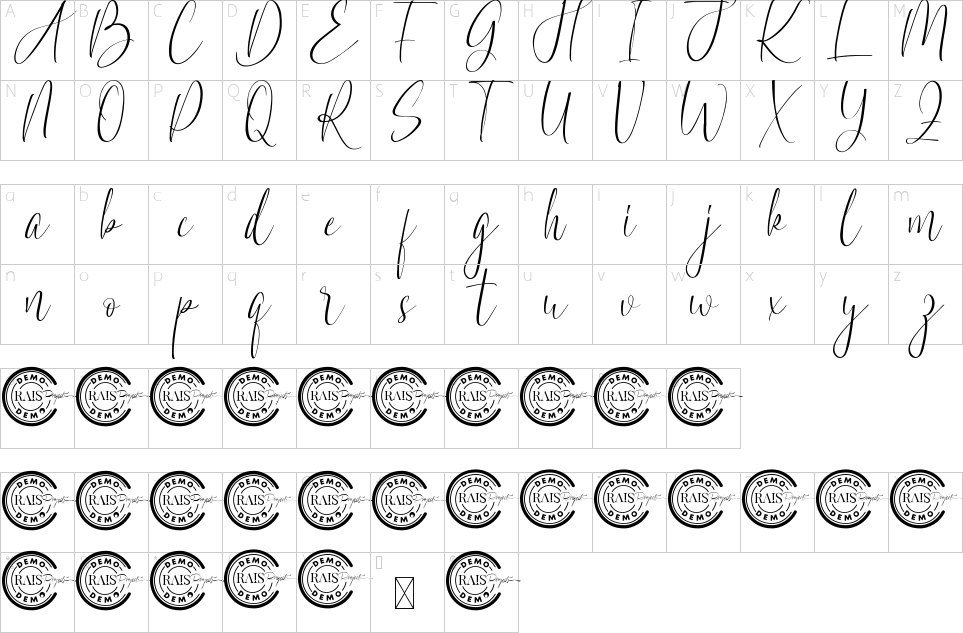
Golden Berry Font – Download Grátis
A Golden Berry é uma nova opção para designers que buscam uma fonte clara e elegante, ideal tanto para projetos digitais quanto impressos. Desenvolvida pela RaisProject, esta fonte gratuita está disponível para quem gosta de dar um toque sofisticado às suas criações. Se você busca uma fonte com estilo minimalista que se adapte a diversos estilos de design, o Golden Berry é um excelente escolha. Esta elegante fonte vem em versões compatíveis tanto com Windows quanto Mac, tornando-a extremamente acessível para designers que trabalham em qualquer plataforma. Ainda não experimentou sua versão gratuita? Seu interesse pela qualidade e a praticidade desta fonte provavelmente serão surpreendidos. Com seu design minimalista mas sofisticado, é perfeito para criar gráficos profissionais sem grandes investimentos. O rastreador uniforme da Golden Berry ajuda em textos legíveis, mantendo um equilíbrio entre leitura confortável e elegância visual, tornando-a uma fonte bastante versátil. Ainda não experimentou a experiência de usar esta fonte gratuita? Aproveite e se surpreenda com o seu poder de design!